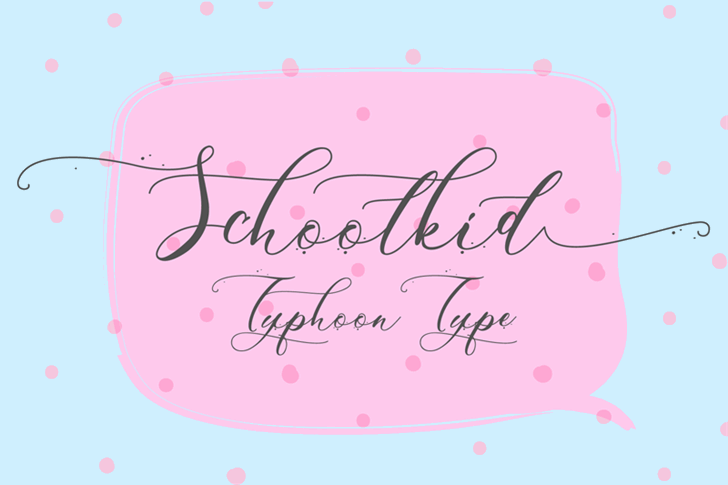
Schoolkid Script Font Family – Download Grátis
A Schoolkid é uma nova fonte escrita a mão apresentada pela Gfont, criada pelo designer Typhoon Type – Suthi Srisopha. Esta fonte é puramente resultado de escrita manual e possui um cariz natural que se assemelha à forma como crianças escrevem em casa. A Schoolkid foi projetada para abordar uma variedade de usos, incluindo cartões de convidado, assinaturas, blogs, mídia social, cartões de negócios e marcas de produto. É perfeitamente adequada para estilos que exigem um toque casual e pessoal, tornando-a ideal não apenas para designers gráficos e criadores de conteúdo online, mas também para aqueles que desejam adicionar um toque especial em suas criações digitais.